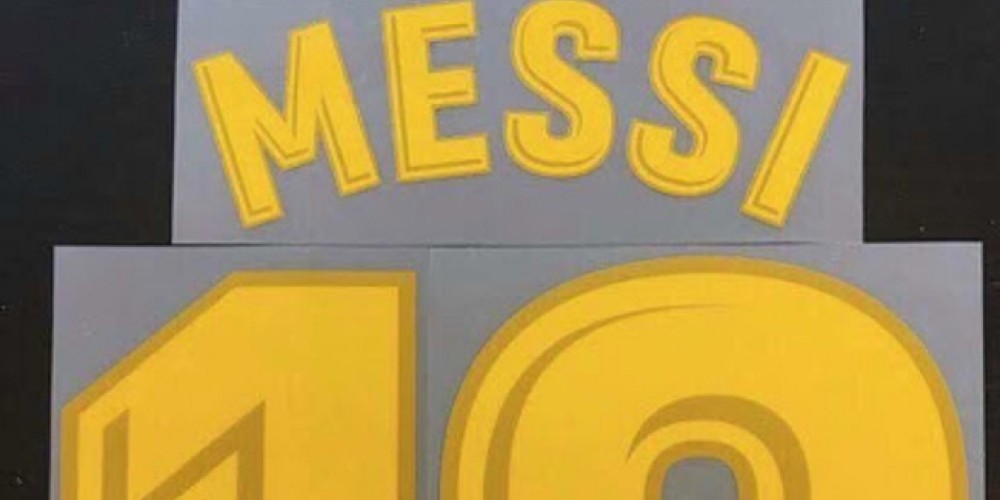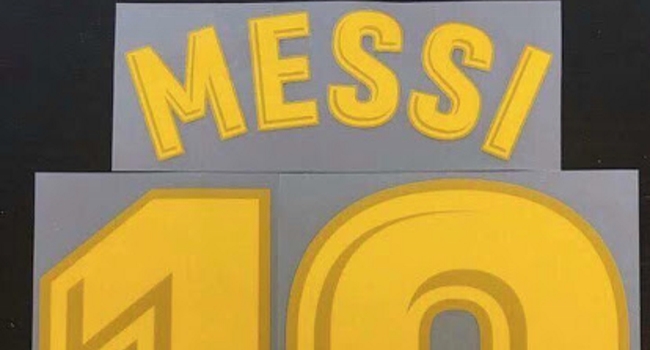
A semanas de lo que fue la consecución de LaLiga por parte del Real Madrid, los organizadores de la competencia ya se enfocan en lo que viene, y es por eso que esta semana revelaron los patrones bajo los cuales se diseñará cada camiseta en función al nuevo modelo de nombres y números a partir del mes de julio.
Inspirados en lo que fue el relevamiento de diseños por parte de la Premier League, MLS y Ligue 1 francesa, el certamen español presentó un innovador y llamativo modelo que según muchos toma algo de lo que fueron los dorsales empleados por el FC Barcelona hasta el 2015.